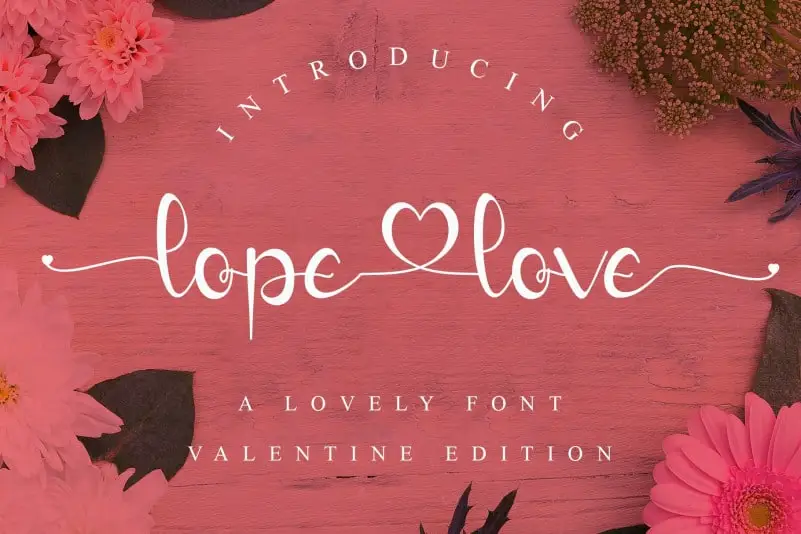
lopelove Calligraphy Font – Download Grátis
A lopelove Calligraphy Font é uma tipografia floridamente decorativa projetada para levar seu projeto a um grau mais elaborado de elegância. Esta calligrafia floral não apenas é perfeita para criar logos e projetos de marca, mas também se adequa à design de móveis de casa, embalagens de produtos, t-shirts, revistas, cards de convite e cartões de visita. Suas letras delicadas são capazes de dar vida a qualquer projeto que necessite um toque suave de elegância, seja para os mais simples ou complexos. A lopelove é uma ótima escolha para aqueles buscando adicionar um toque personalizado e sofisticado aos seus projetos gráficos. Seja o próximo seu favorito para criações que valorizam a harmonia entre arte e funcionalidade.